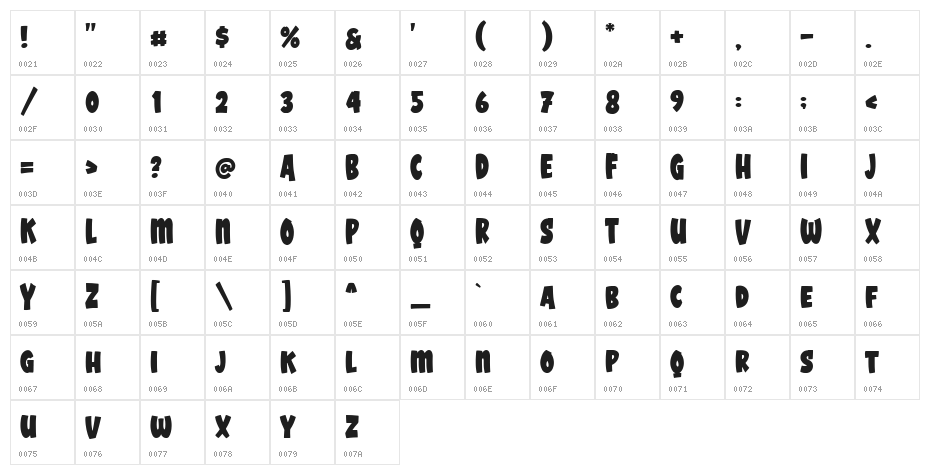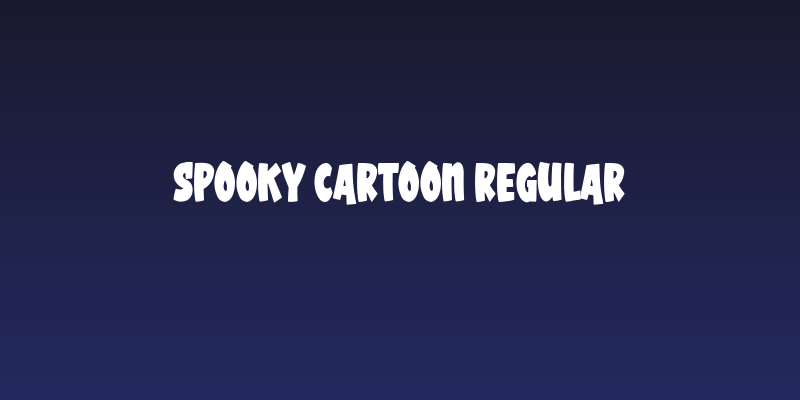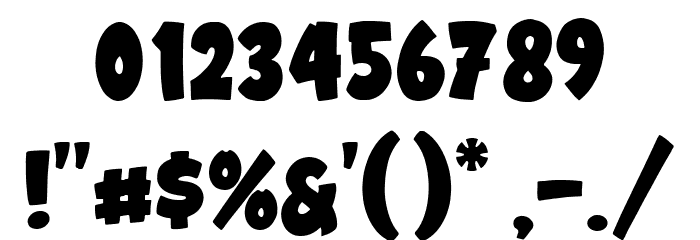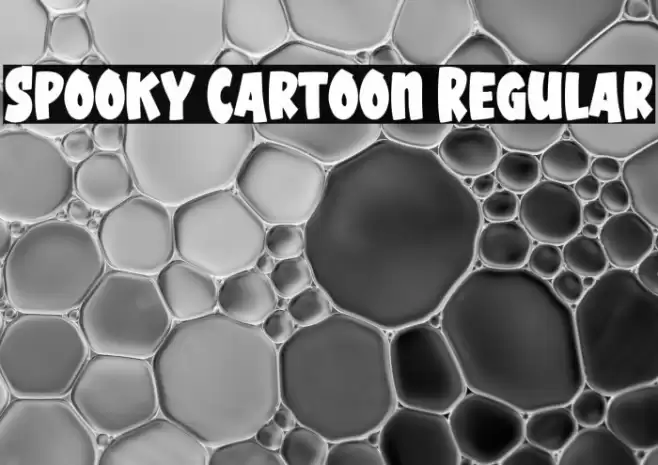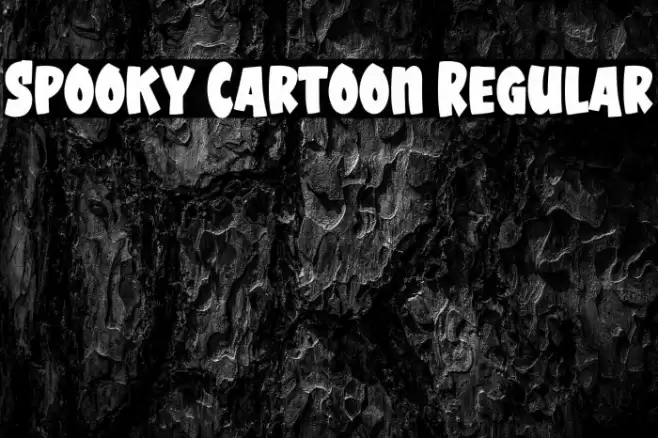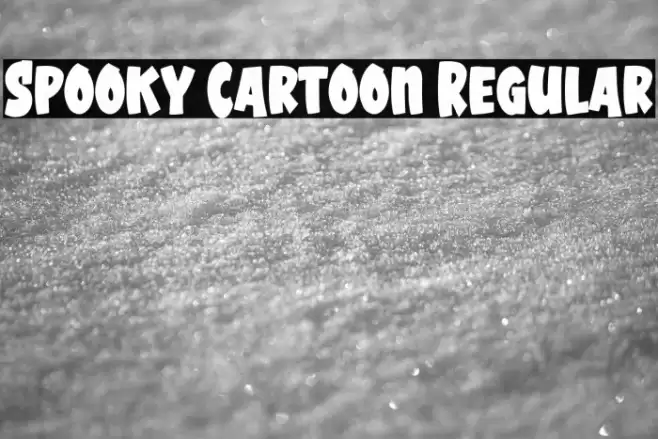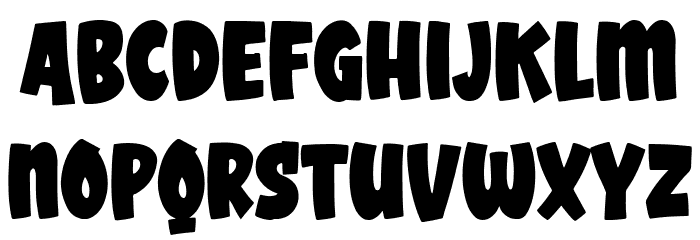
Spooky Cartoon Regular Font
| 名前 | Spooky Cartoon Regular |
| フォントファミリー | Spooky Cartoon |
| 全体的なスタイル | Playful, Cartoonish, Whimsical |
| 用途 | Headlines, Logos, Posters, Invitations |
| おすすめプロジェクト | Ideal for children's books, Halloween-themed designs, comic strips, playful branding, and party invitations. |